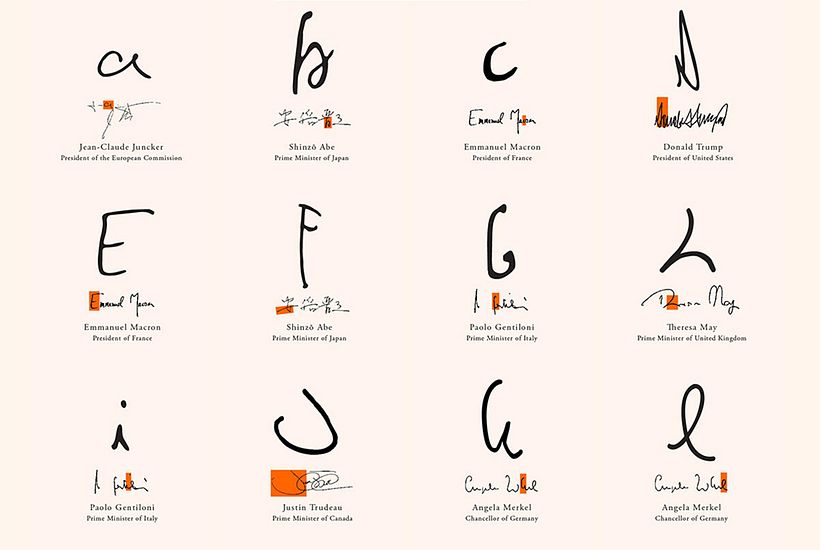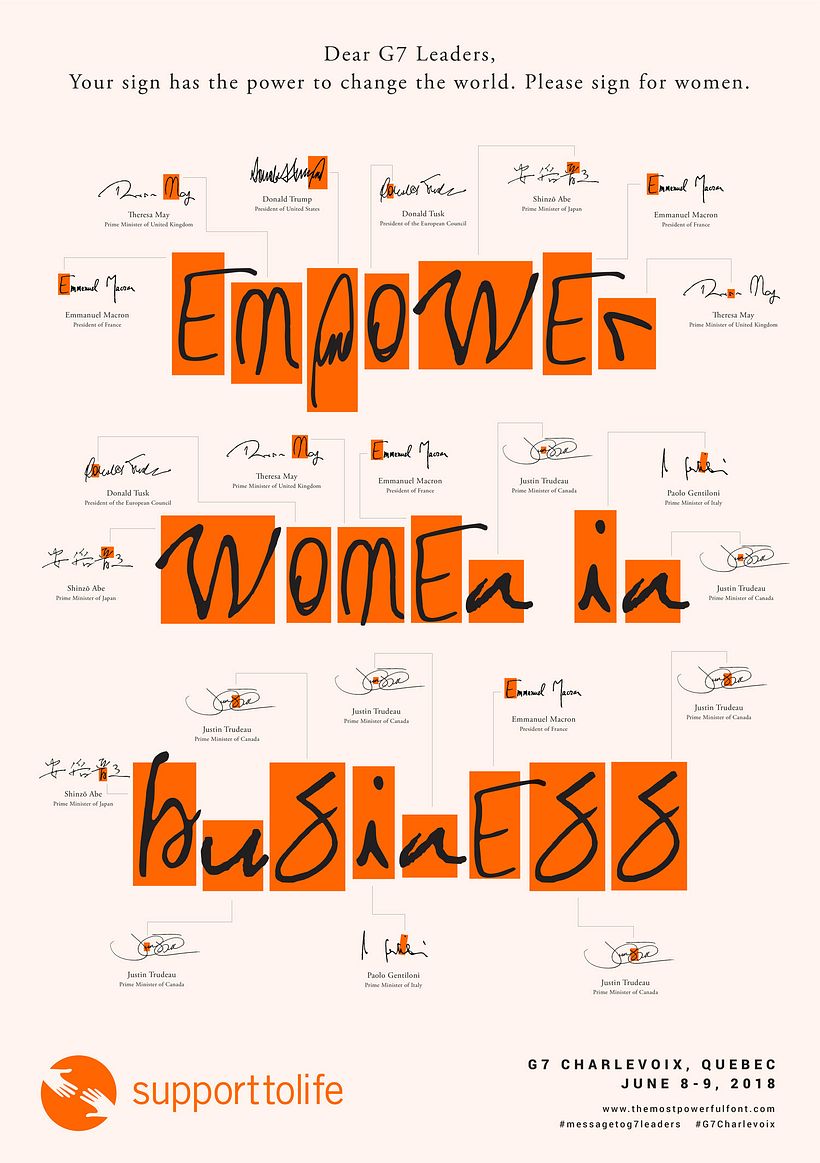
Esta es la tipografía más poderosa del mundo
The most powerful font ha sido diseñada a partir de las firmas de los representantes de los países que integran el G7.
Que el diseño es una herramienta poderosísima para comunicar y reivindicar es algo que resulta indiscutible, y por eso es constante la aparición de iniciativas que lo utilizan como medio para llamar la atención sobre ciertas problemáticas y reivindicar la atención pública en busca de soluciones. Uno de los últimos proyectos que han utilizado el diseño como instrumento de conciencia social es The most powerful font, una tipografía cuyos caracteres han sido diseñados a partir de las firmas de los representantes de los países que forman el G7.
El G7 está formado por siete países cuyo peso político, económico y militar es especialmente relevante a escala global y es por eso que sus autores decidieron bautizarla como "la tipografía más poderosa del mundo". Detrás de esta campaña se encuentra la agencia TBWA\Istanbul, que decidió llevar a cabo esta iniciativa con la vista puesta a la 44ª cumbre que se celebró en Quebec (Canadá) a principios de junio.
Utilizando las rúbricas de personalidades políticas de los siete países que actualmente forman el G7 –Alemania, Canadá, Estados Unidos, Francia, Italia, Japón y Reino Unido– diseñaron una tipografía única que, aunque quizás no destaca por su extrema belleza, sí es importante por el mensaje que quiere lanzar. El mensaje que The most powerful font quiere lanzar es el de que la firma de los representantes de algunos de los países más poderosos del mundo tienen una importancia crucial en el desarrollo de la sociedad y en problemas globales tan preocupantes como las crisis migratorias y el deterioro del medio ambiente. Por eso, la campaña no se ha limitado a diseñar la tipografía y distribuirla, sino que pretende servir como altavoz a los ciudadanos para que puedan hacer llegar sus peticiones a los tomadores de grandes decisiones del mundo.